Wie schön! oder Zu viel des Guten?
Wie schön!, war mein erster Gedanke beim Auspacken der Bielefelder Bibel. Kein Leichtgewicht, aber angemessen für ein Werk von Gewicht, und so austariert, dass die haltende Hand beim Lesen weiß, dass sie ein bedeutendes Buch hält. Ein angenehmer Leineneinband, fühlt sich echt an, angenehmes Papier und ein Seitenformat mit Platz.
Wirklich ästhetisch ansprechend. Dieses Buch unterstützt den Gestus des Lesens (ein besonderer Dank gebührt hier Klaas Huizings Ästhetischer Theologie fürs Augenöffnen).
»Die heilige Schrift in lesefreundlicher Form« – in Broschüren und im Nachwert eine markante Spur zu großspurig formuliert – für das Exterieur dieser Bibelausgabe mag ich das ganz und gar gelten lassen. Aber ich vermisse dabei die Demut vor der Geschichte der Buchherstellung und Typografie: Viele haben bereits großartiges geleistet, mit dem Rohr, der Feder, dem Blei. Mag im modernen Bibeldruck auch das meiste verschütt gegangen sein, es geht schlicht nicht um Neuerfindung sondern um Anschluss an die alte Schwarze Kunst. Geschenkt.
Ich beginne vorne zu blättern. Schöne Schrift. Die FF Nexus von Martin Majoor. Schöner Rhythmus, offene Formen, nicht zu eng, genügend Luft dazwischen – für den Geist, der ja auch wehen muss bei all den Buchstaben.
Was gleich auffällt: Das sekundäre Ordnungssystem hält sich maximal zurück! Endlich! Eine Bibel tatsächlich zum Lesen! Genaue Versangaben finden sich nur unten auf der Seite – so weit unten, dass klar ist: darum geht es nicht. Als wirklich dienende Marginalien nur die Kapitelziffern am Rand, ich bin begeistert! Mission erfüllt: Nicht stören! (Bild 06)
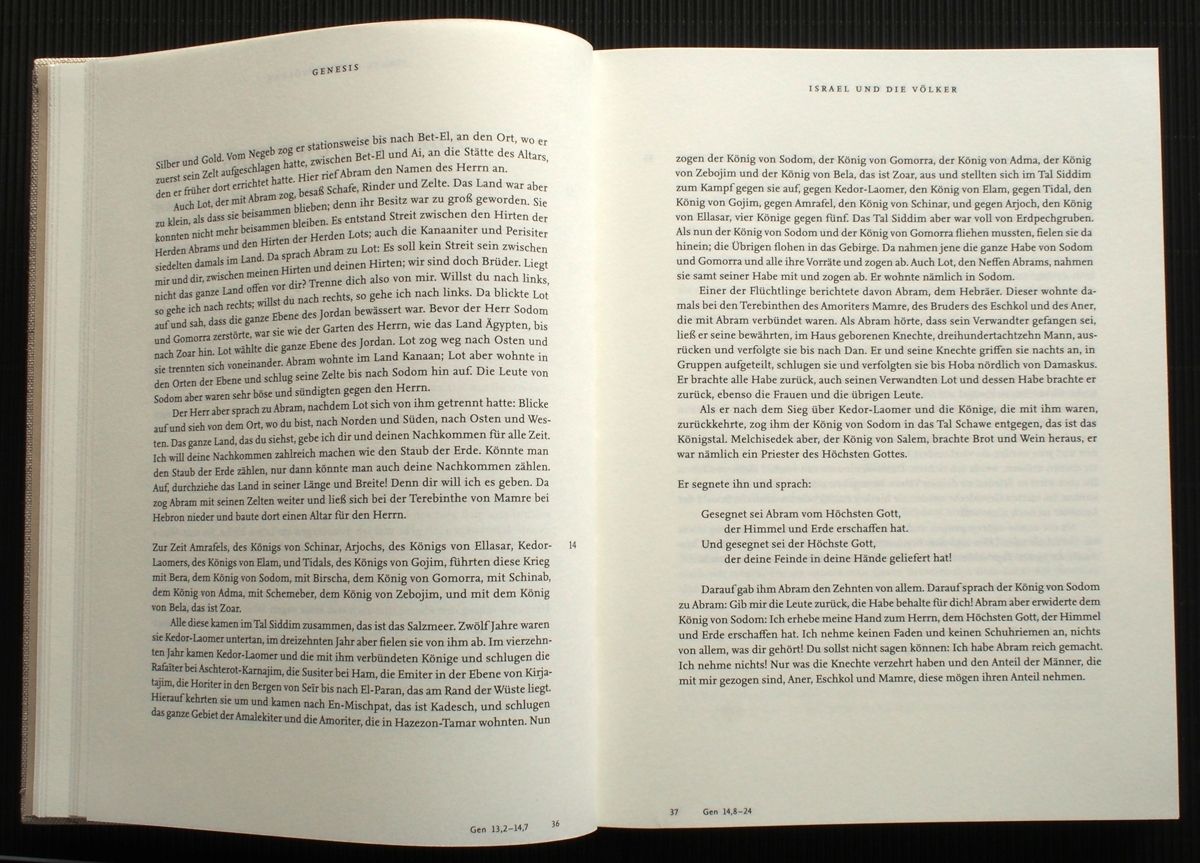
Im Weiterblättern zeigt sich: Verschiedenes ist eingesetzt worden: Initialien, überformte, gedichtete Texte in besonderer Zeilenanordnung, beeindruckend stimmiger Einsatz von Kapitälchen, zurückhaltend hie und da Marginalien, so gut wie keine Zwischenüberschriften (die es im eigentlichen Bibeltext ja nicht gibt). (Bild 09, 10, 13, 22)
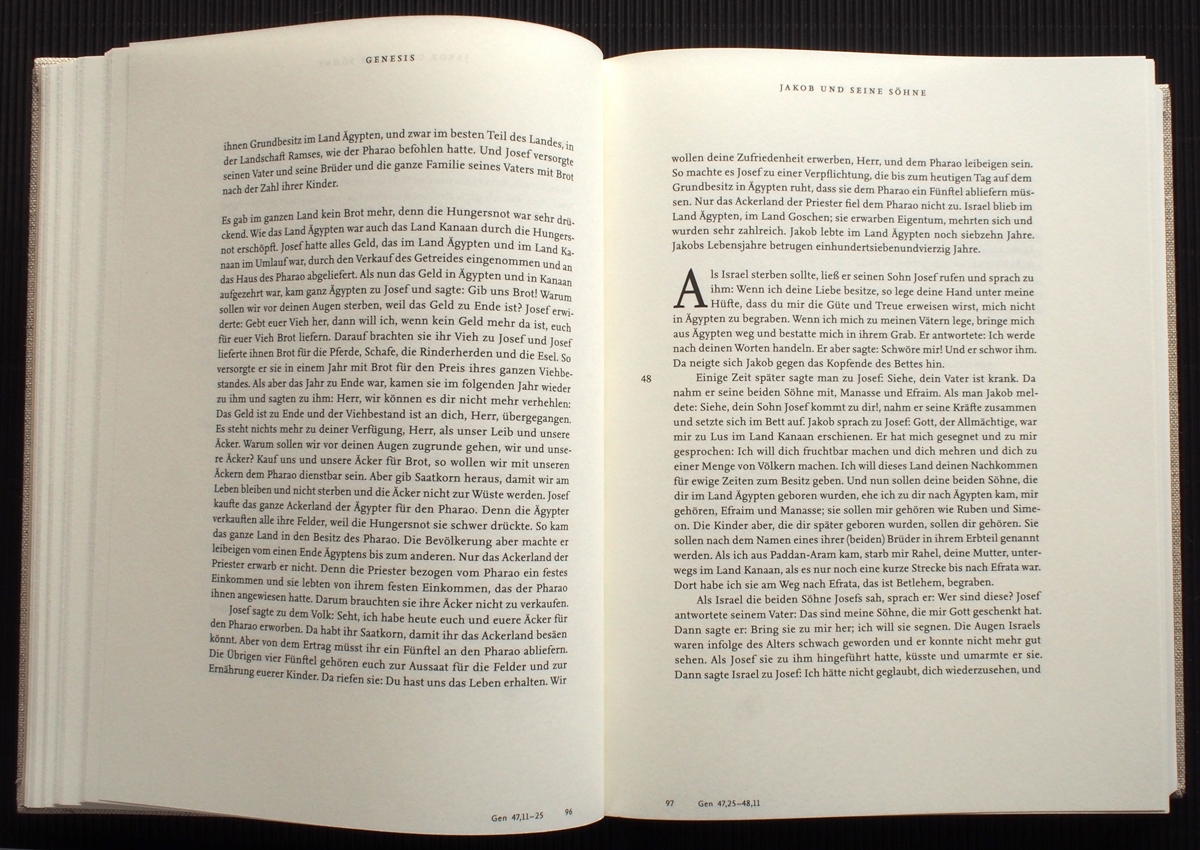
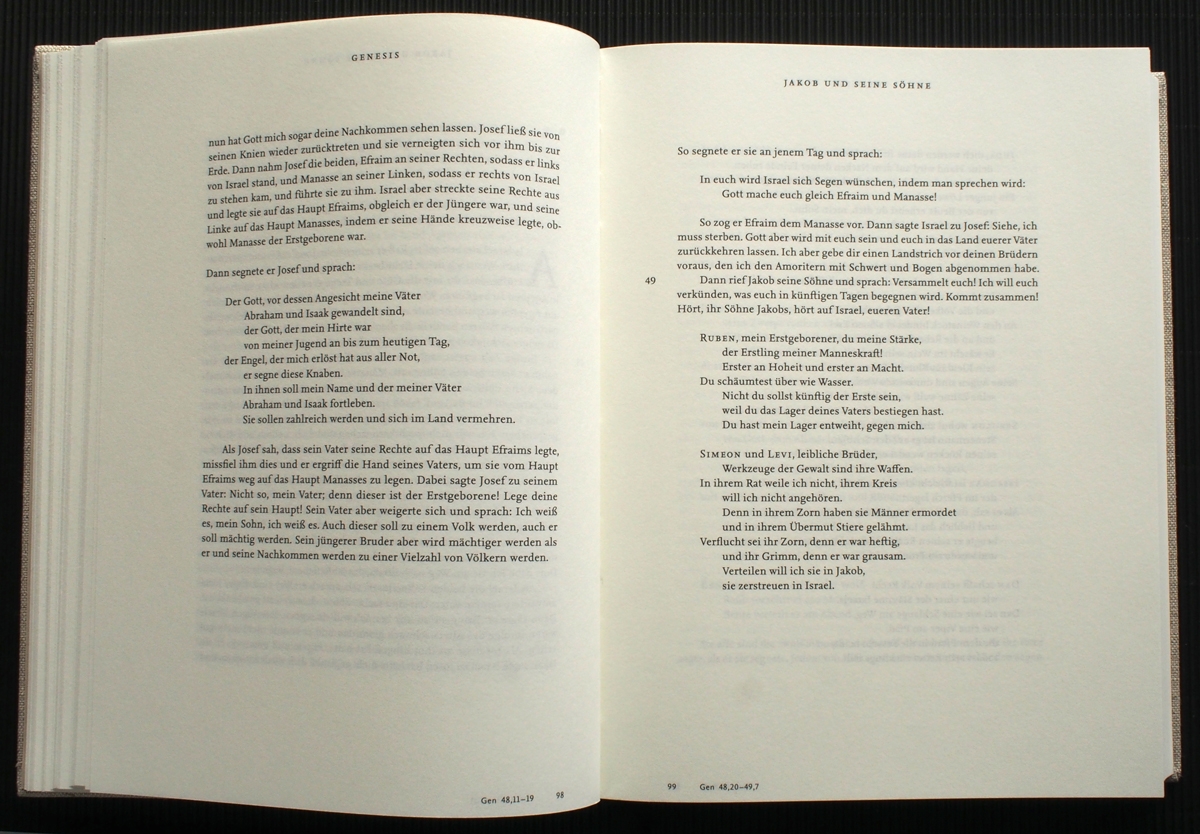
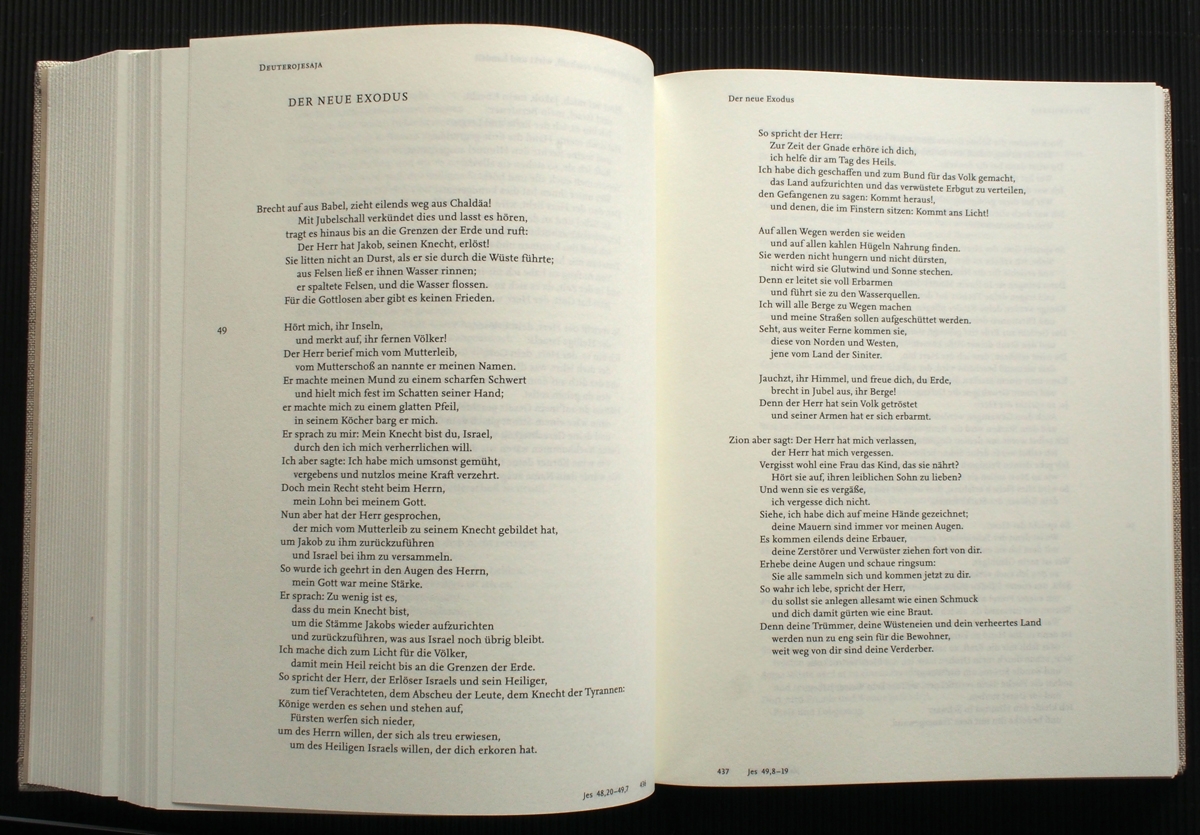
Weiter: Ein paar spannende Weisen, die Seite aufzuteilen, Dialoge zu setzen (Hiob). (Bild 16)
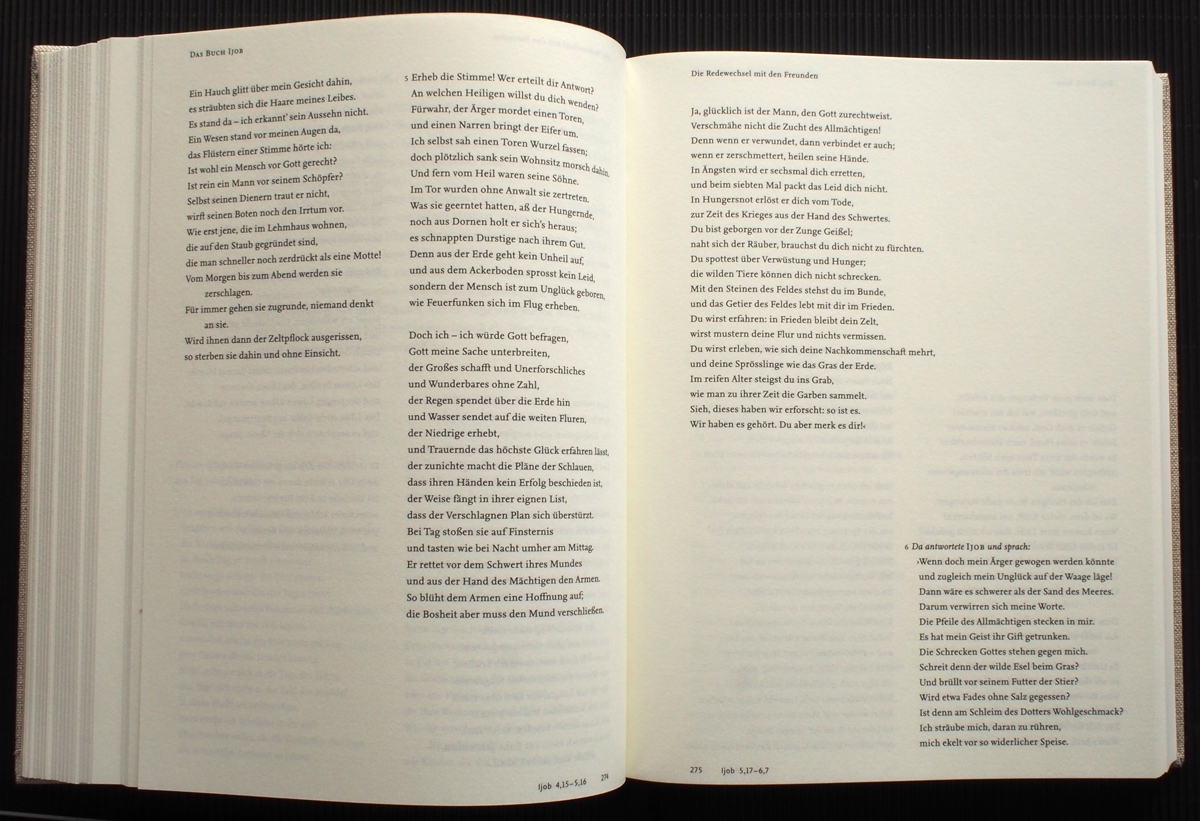
Die Psalmen: Hierfür gleich mal ein besonderer Dank! Das sind Liedertexte, außer der Psalmnummer haben (und brauchen) sie keine Versziffern. (Bild 21)
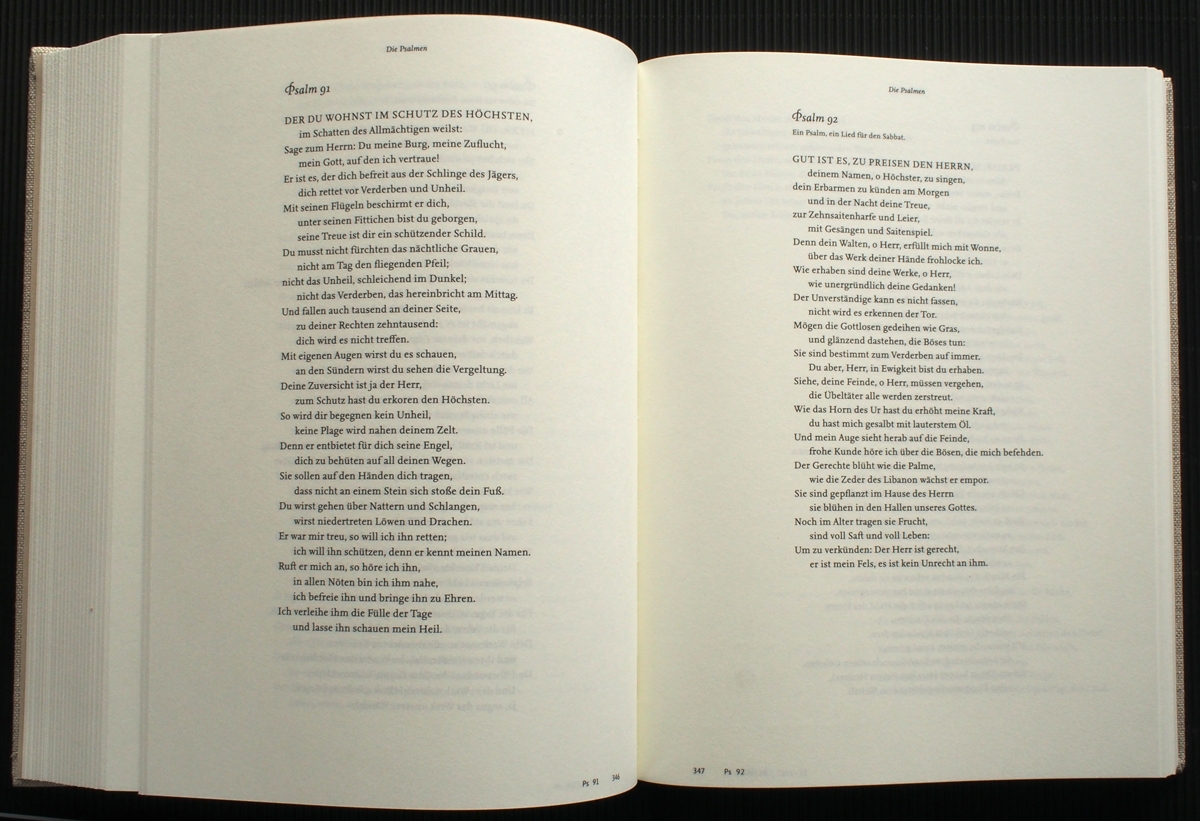
Die Spruchsammlung: Erfrischend, sie einmal tatsächlich wie eine Sammlung aufgemacht zu sehen! (Bild 20)
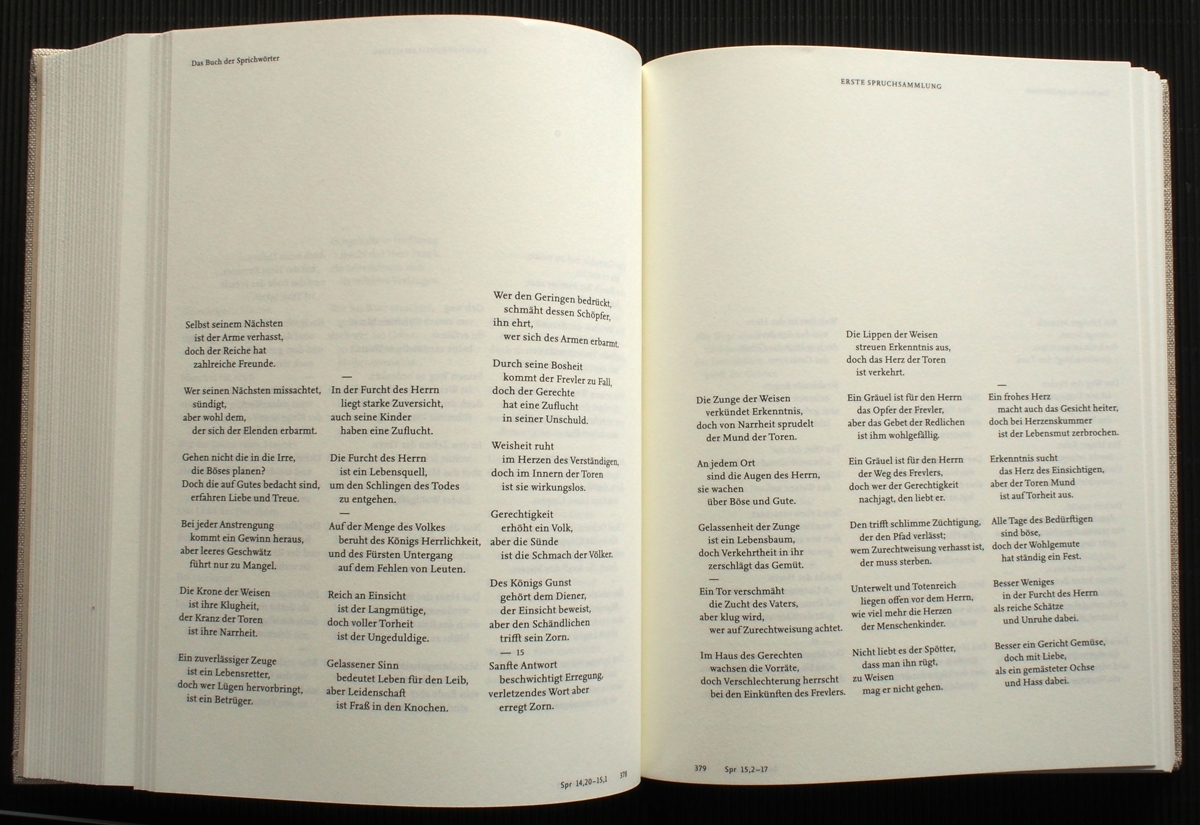
Ich bin schon durch die Hälfte durch und habe bisher weniger Ziffern gesehen als sonst auf den ersten zwei Seiten. Ja, so kann sich Hören einstellen darauf, was der Text zu sagen hat – und was ich dazu sage.
Eine erste Irritation trifft mich auf Seite 449 (von 688): Das Buch Jona. Ich habe plötzlich ein anderes Buch vor mir. Jona ist gesetzt wie ein Kinderbuch: In großer Schrift mit riesigem Durchschuss. Ich fange geradezu das Buchstabieren an. Mir fällt eines meiner ersten Kinderlesebücher ein. (Bild 23)
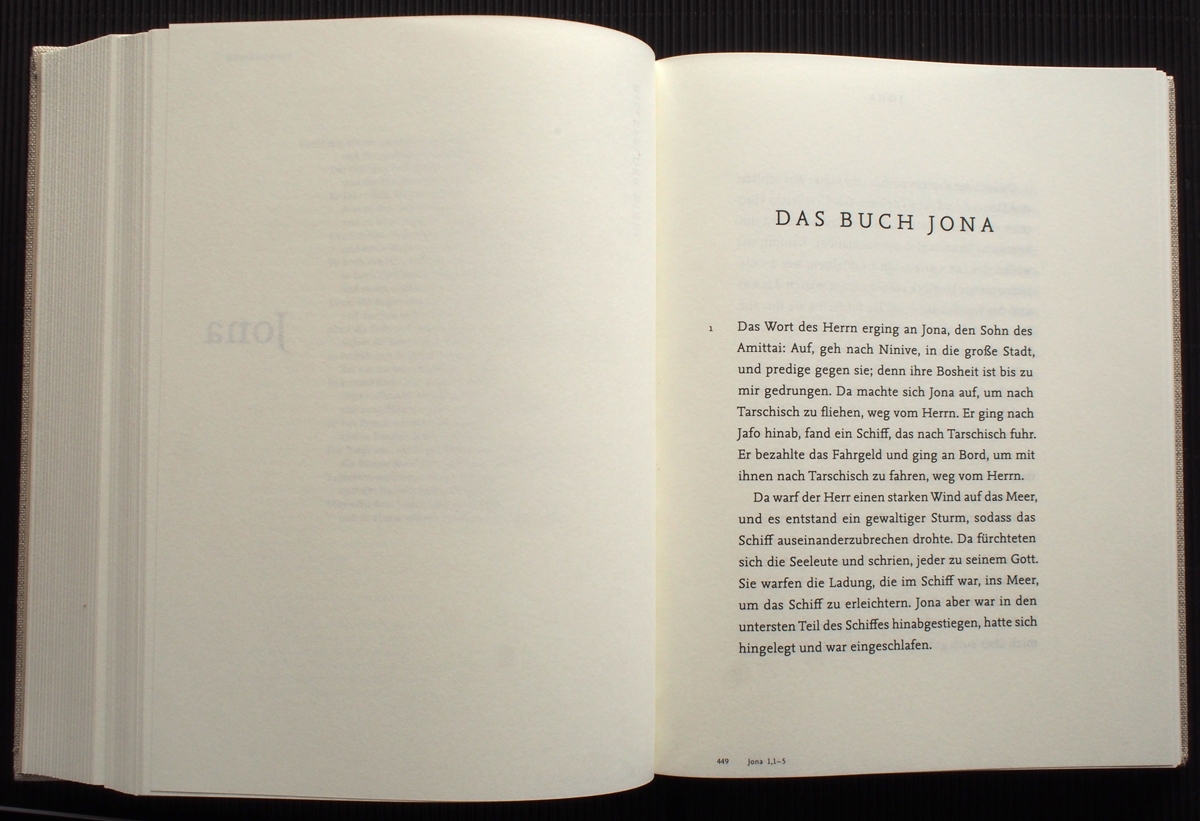
Danach geht es wieder normal weiter. Geradezu ein Aha-Erlebnis ist für mich der Satz der Bergpredigt: Typografisch mit hängendem Einzug wird die Zusammenstellung verschiedener kurzer Redeeinheiten so überzeugend markiert, dass die sonst üblichen (sekundären!) Überschriften gar nicht fehlen. Im Gegenteil: Ich will solche nie wieder sehen, sie zerlegen den Text. Hier bleibt er bestehen. (Bild 27, 28)
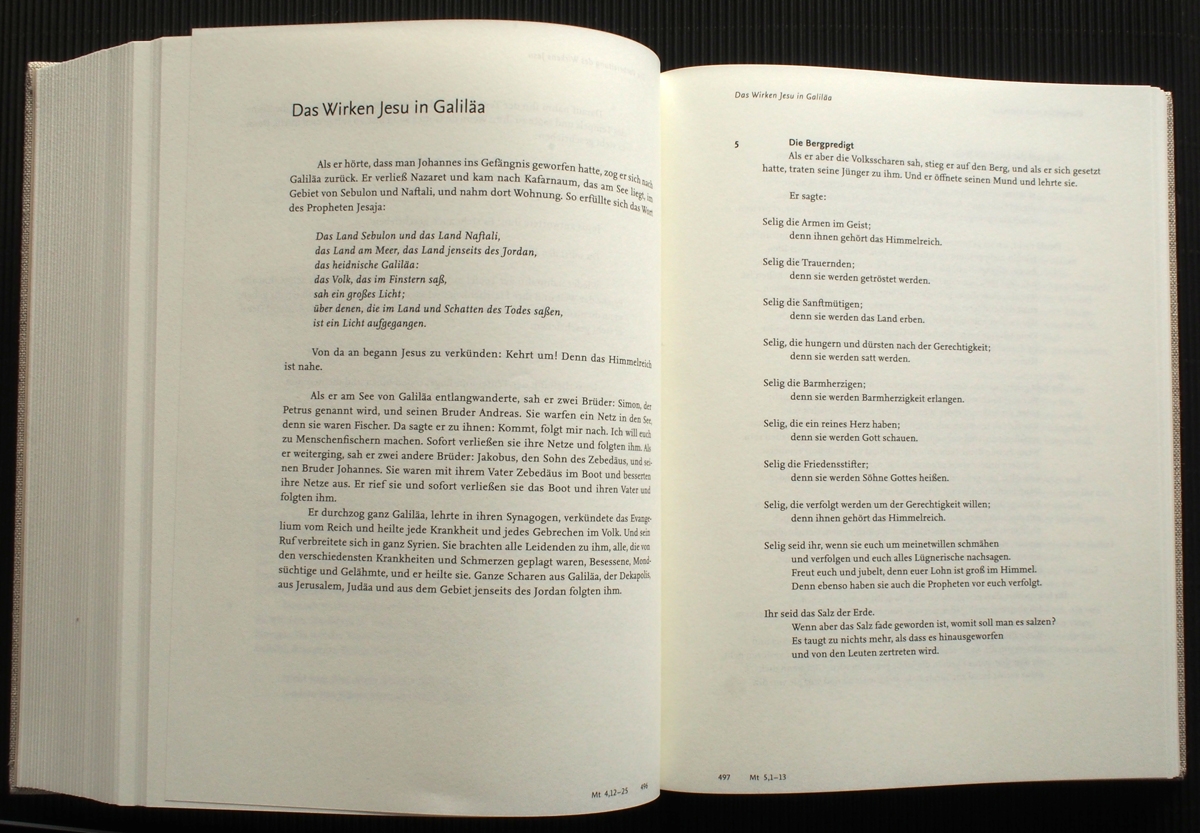
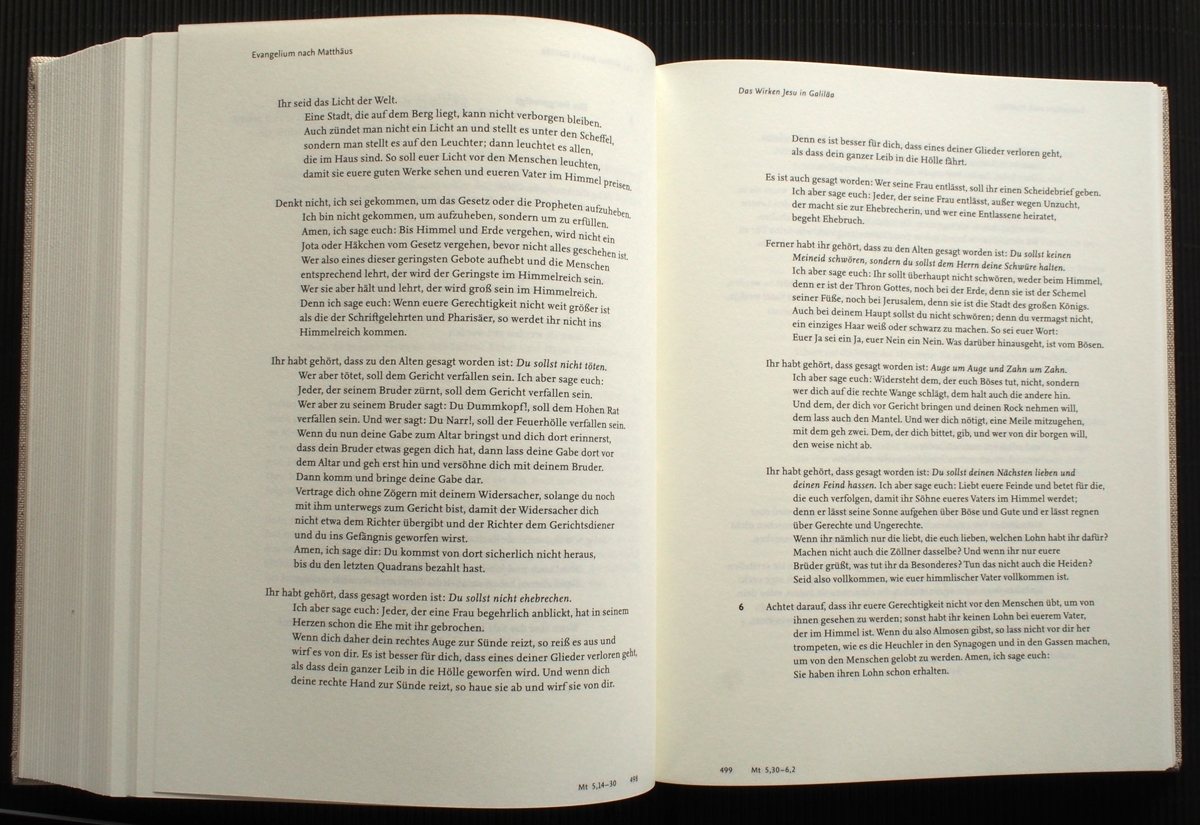
Bei den Briefen dann wieder ein optischer Anstoss: Sie sind monospaced gesetzt. Wie einer der alten Schreibmaschinenbriefe, als „Gemeindebrief“ noch tatsächlich ein Brief war. (Bild 31)
Die Offenbarung: Sie zeichnet sich inhaltlich ja schon durch kräftige Kontraste aus. Die Typografie tut das mit normalem und fettem Satz (nicht halbfett!) ebenso. (Bild 32)
Ich habe nach diesem Durchgang eine ganze Menge interessanter Lösungen und auch ein paar weniger überzeugende Stellen überflogen. Es lohnt sich, das genauer in den Blick zu nehmen.
Eine interessante Lösung haben die Macher der Bielefelder Bibel gleich zu Beginn der Bibel gewählt: Der erste Schöpfungstext schildert in stark überformter Sprache eine Abfolge der Schöpfung der ganzen Welt, eingeschrieben in die sieben Tage der Woche. (Bild 01)
»Es werde Licht! – und es ward Licht« ist ein starkes und ein bekanntes Stück Sprache. In der Bielefelder Bibel wird für jeden dieser Tage und sein Werk eine eigene Seite verwendet und der Schöpferbefehl in großer Versalienschrift ins Zentrum gestellt. Gesetzt in Zentralachse blättert man erhaben durch die Tage – um aber am siebten Tag … auf nichts zu stoßen. Ja, nichts, denn an diesem Tag ist nichts hervorgehoben. Das, was Gott tut – nämlich ruhen – war in den Augen der Bielefelder offenbar nicht gleichauf mit den sechs Schöpfungswerken zuvor. Die Seite wirkt so wie eine Fußnote, ein Impressum vielleicht, jedenfalls nichts bedeutendes. (Bild 02)
Aber wer sich ein bisschen auskennt, weiß: Der siebte Tag wird zum Ruhetag, der sogar in die zehn Gebote aufgenommen wird. Die Ruhe gehört zu Gottes Schöpfungswirken hinzu und er befiehlt sie den Menschen ausdrücklich an. Sie ist die Luft, die der Mensch zum Leben braucht. Folgt man aber den typografischen Signalen, geht es in der Schöpfung allein um das Tun, das, wo etwas dabei herauskommt. Und das ausgerechnet in einer Zeit wie der heutigen, die dringend den fest eingeplanten Freiraum bräuchte, der die Entschleunigung durch einen Ruhetag gut täte?
Hier zeigt sich ein erster Fallstrick typografischer Inszenierung: Die Typografie ist beeindruckend, aber sie geht am Duktus des Textes vorbei, verführt geradezu dazu, das Entscheidende nicht mitzubekommen. Und Beispiele für ein solches Vorbeigehen finden sich noch einige:
Eine kleine Irritation ergibt sich im weiteren Verlauf bei den sogenannten Geschlechtsregistern, Aufzählungen von Abstammungen. Sie sind mit doppeltem Zeilenabstand in den Text gesetzt und so abgehoben. Das Problem dabei: Die das Lesen verlangsamende vertikale Sperrung suggeriert, dass es sich hier um gegenüber dem Kontext wichtigere Texte handelt. Das aber ist nicht der Fall und kostet die Erzählüberlieferung drumherum und dazwischen viel Aufmerksamkeit. (Bild 08)
Springen wir ein gutes Stück weiter zu den Zehn Geboten: Diese werden hier auf einer Doppelseite in Zentralachse gezeigt. Was aber besondere Wirkung auslöst, ist der Meta-Satz: Die Gebote sind hier mit großen römischen Ziffern nummeriert. (Bild 12)
Im Originaltext gibt es diese Ziffern nicht. Sie geben den Zehn Geboten, die hier eigentlich in eine Rede eingebettet sind, eine sehr juristische statische Tonalität. Ist es das? Oder gibt das den Geboten den Sinn, den viele dann für sich ablehnen: Verurteilung?
Eine weitere Differenz zwischen Inhalt und Gestaltung findet sich in Ester: Hier werden über fünf Zeilen reichende Swash-Initialen verwendet. Und so kommt es, dass unter der Überschrift »Die Bedrohung« ein ausgesprochen sinnenfreudiges und beschwingtes N zu stehen kommt. Ist das Fancy-Literatur? Kommt jetzt gleich eine gutaussehende, bewaffnete Heldin ins Bild? möchte man fragen. Die Typografie verbreitet Stimmung. (Bild 15)
Das Buch Ijob/Hiob mit seinen langen Überlegungen ist interessant in korrespondierenden gegeneinander versetzten Spalten gesetzt. So ist das durchaus gut. Aber als Gott anfängt zu sprechen, wird sein Text in mehr als doppelter Schriftgröße gesetzt. Theaterdonner quasi. (Bildfolge 16, 17, 18)
Aber das Aufregende am Hiobbuch ist doch, dass hier erst ein Mensch durchaus aufmüpfig und mit noch heute anstößigen Worten Gott anklagt (der das nach der Vorgeschichte auch verdient hat). Andere das dann relativieren wollen und ihn Gott gegenüber klein machen wollen. Am Ende aber Gott ihn ins Recht setzt, ihm Rede und Antwort steht. Hier aber wird Hiob gegenüber Gott typografisch sehr klein gemacht. Die Spannung ist eigentlich auf Buchstabenebene ausgelöscht. So gesetzt muss man nicht mehr groß nachdenken, es funktioniert auch nicht.
Geradezu verstörend finde ich, was mit dem kleinen Prophetenbuch Jona geschieht: Es ist mit großen Buchstaben und noch größeren Zeilenabständen wie ein Kinderbuch der Grundschule gesetzt. Quasi ein Märchen. Mag ja sein, dass der Walfisch einem nicht realitätsnah erscheint. Aber das sind die Erfolgsgeschichten gestandener Wirtschaftsmanager auch manchmal nicht. Jona wird hier als Kindergeschichte gekennzeichnet. Und leider wird sie in unseren Kirchen meist so verwendet. Aber wer sie genau anschaut, wird bemerken, dass sie sich eigentlich um einen Mann, seine Vorstellungen, Schwächen, Übertreibungen (unter einem Wal gehts nicht) und seine Aggressivität dreht. Schließt man mit Kindertypografie nicht genau diese Rezeptionsmöglichkeit ohne Not von vornherein aus?. (Bild 23, 24, 25)
So ergibt sich der Eindruck, dass die Typografie hier viel mehr in den Bibeltext einträgt, als sie soll und als ihr zusteht.
Um ein Fazit zu ziehen, möchte ich einen Bibelvers heranziehen, der Typografen wie ein Stachel im Fleisch sein dürfte:
»Der Buchstabe tötet, der Geist aber macht lebendig«, sagt Paulus.
In der Bielefelder Bibel sind es die Buchstaben und ihre Verwendung, die an nicht wenigen Stellen dem Text eine eigene Deutung aufdrücken – und so die Freiheit des Geistes einschränken. Eine zurückhaltende typografische Unterstützung zum Beispiel dichterischer Sprache ist freilich angemessen, hier ist aber oft zu viel des Guten getan worden.
Die Typografie sollte sich generell nicht vor ihren Text stellen, sondern ihm dienen und sich selbst nach Möglichkeit unsichtbar machen. So wie das schon mit den Ziffern der Verse und Kapitel geschehen ist. Insofern ist die Bielefelder Bibel nach wie vor ein schönes Buch, auch ein beeindruckendes Werk typografischer Möglichkeiten, aber nur bedingt tauglich als Muster für lesefreundliche Bibeln.
Die Suche nach einer qualitativ ausgezeichneten heutigen Bibeltypografie ist noch nicht abgeschlossen. Danke aber dennoch für (mindestens) vier Sachen: Den Satz der Psalmen, die Sprichwörter und die Bergpredigt. Und vor allem: Für die Zurücknahme der Ziffern und nicht-originalen Texte.